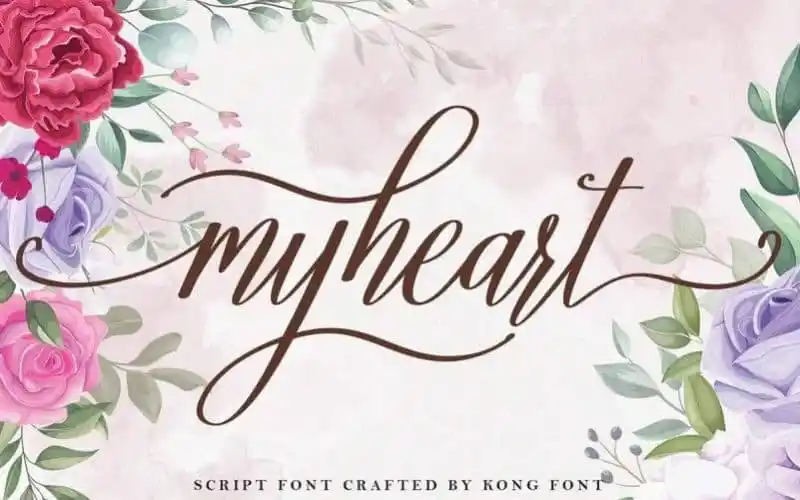
Myheart Calligraphy Font – Download Grátis
Myheart Calligraphy Font é uma fonte elegante e natural criada pelo designer Kong Font, ideal para quem busca personalidade única em seus projetos digitais ou impressos. Com sua abordagem minimalista que carrega um toque angelical, esta fonte é perfeita para qualquer uso, seja em sites, marcas nas redes sociais, banners no Pinterest, convites impressos ou outros materiais de marketing digital. Suave e envolvente ao mesmo tempo, ela oferece uma variedade incrível de possibilidades para personalizar seus projetos com estilo e sofisticação. Experimente Myheart Calligraphy Font em seu próximo projeto e descubra como pode transformar a forma que você expressa sua identidade visual.